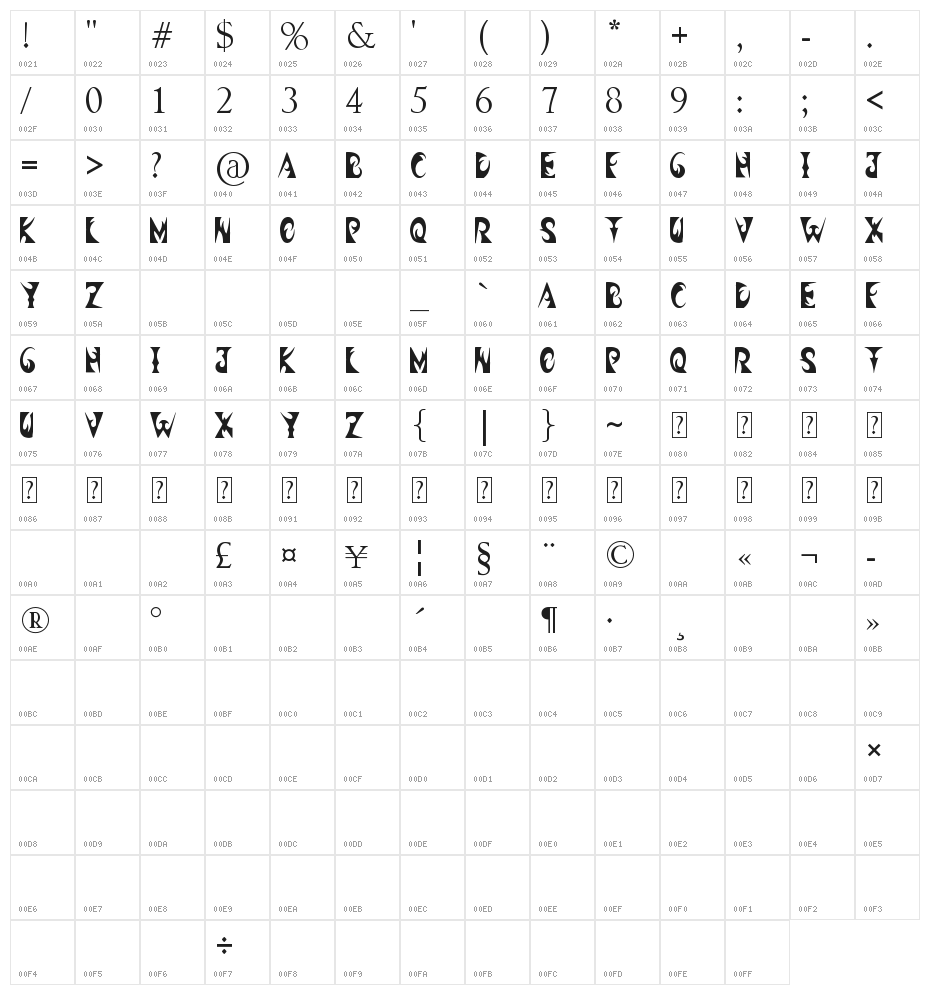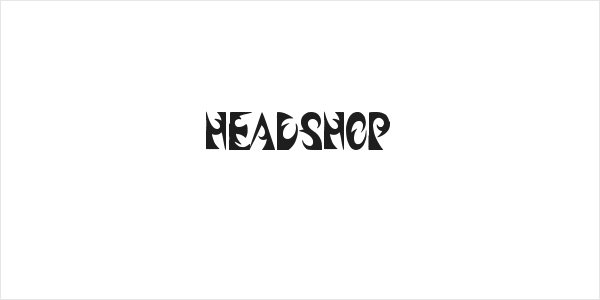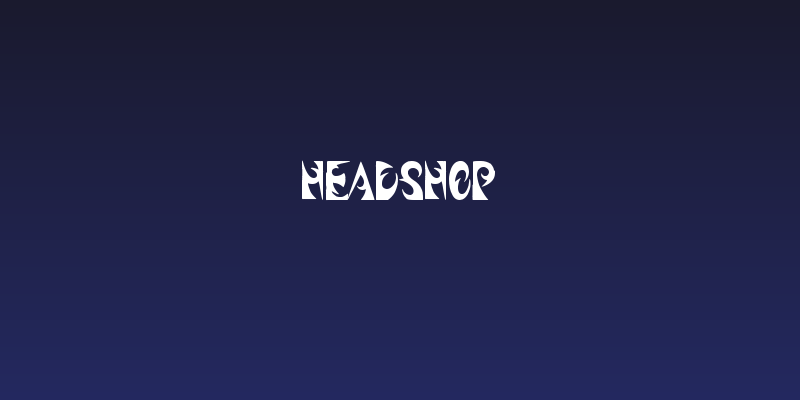
Headshop Font
✎ Curly
| Vorgeschlagene Projekte | This font is perfect for album covers, posters, branding for edgy or alternative products, and any design project that requires a bold, eye-catching typeface. |